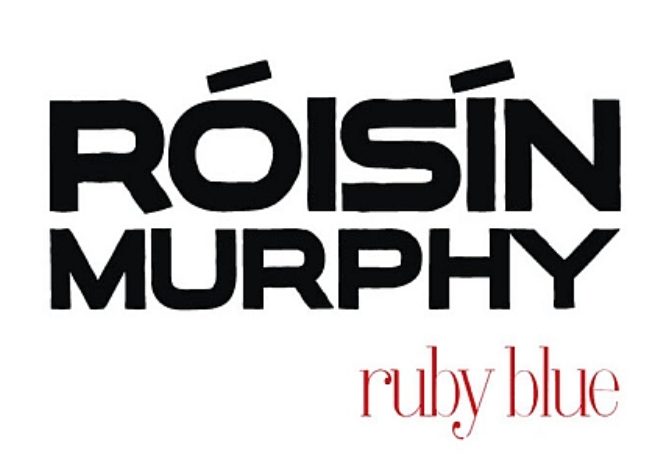
Róisín Murphys "Ruby Blue" - zwei Schriften gesucht
Ich suche die beiden Schriften des Albumcovers von Róisín Murphys "Ruby Blue" aus dem Jahr 2005, einmal eine Grotesk- (nur versal für Róisíns Namen verwendet) und eine Serifenschrift (Minuskel für den Titel).
In den Credits wurde Steffan MacMillan als Designer des sleaves angegeben.
Diesen habe ich auf Twitter gefunden.
Er ist einer der Gründer vom Alphabetclub und hat netterweise auf meine Anfrage reagiert. Mit diesem Stand der Dinge wende ich mich nun an euch, denn die Namen der Schriften konnte ich trotz "Urheber" nicht herausfinden.
Die Schriften stammen also laut Aussage MacMillans aus einem alten, französischen Magazin, welches er teilweise gescannt und für Namen und Albumtitel nachgezeichnet hat.
Es ist also anzunehmen, das es ebenso französische Schriften sein könnten. Ich persönlich würde vom Erscheinungsbild der Schriften einen Zeitraum von 1960er bis 1980er eingrenzen.
Da sie aus einem publizierten Magazin stammen, nehme ich an, dass diese auch irgendwo digital und somit kommerziell erhältlich sein müssten. Parallel zu diesem Beitrag werde ich die französischen Einträge im Type Foundy Archive durchforsten.
Eine Anmerkung: Je nachdem, wann genau das Magazin publiziert wurde, kann es durchaus sein, dass die Schrift nicht digital vorliegt, sondern beispielsweise im Fotosatz realisiert wurde. Das Wort MURPHY sieht übrigens sehr nach einer (etwas ungelenk) manipulierten Satzschrift aus, da würden sich recht schnell ähnliche Vorbilder finden lassen – aber nach dieser hast Du ja nicht gefragt, richtig?
Hier für die Kollegen der Einfachheit halber die Abbildung der gesuchten Schriften direkt eingebunden, das erleichtert die Suche:
Und bei der RÓSÍN erscheint es mir auch fraglch, ob es hierzu überhaupt passende Gemeine gibt. Ich habe ja schon einiges ähnliches umgesetzt, und da gibt es dann bei einigen Minuskeln echt Probleme, die in die Formensprache vder doch recht fetten Schrift zu prügeln. nAllerdings ist die Konstrultion dieser Schrift so deutlich in den vorhandenen Buchstaben erkennbar, das man son etwas wohl schneller komplett sauber zeichnet, als sie in Schriftverzeichnissen zu suchen.
Und wenn der Designer des Covers die auch schon lieber nachgezeichnet, oder sonst wie reproduziert hat - was dann zu diesem etwas ungelenken führt, denke ich, dass auch der schon vergeblich gesucht hat.
Ich muss da an die Schrift Good Times von Typodermic (1998) denken.
Die Schrift hat eine gewisse Ähnlichkeit und ich hatte die mal im Auge, eben weil ich nach so was wie einer Vorlage gesucht habe, aber über die grundlegenden Vorlagen und Ideen zur Good Times keinen Schritt und keine Schrift weiter gekommen bin. Ich war mir ziemlich sicher, das es eine Art Vorlage, wie Du sie hier gezeigt hast geben muss. Deine Vorlage ist für mich so was wie das "missing link", nach dem ich vor einigen Wochen erfolglos gesucht habe. Das wird Dir zwar nicht weiterhelfen, aber mir hilft Deine Anfrage weiter. Danke schön.
ähnliche schriftens gibts eigentlich wie sand am meer.
ich bezweifle das du genau diese zeichen als font finden wirst,
vorallem solange wir nicht erfahren ob es der titel oder eine
headlineschrift in diesem 'magazin' war, bzw. wie dieses hieß.
das an den buchstaben herumgeschnitzt wurde, sieht man ja
schon beim R.
Schade, natürlich. Der Designer meinte, man hätte ihm eben dieses alte Magazin "hingeworfen" und hat damit gearbeitet.
Die Good Times Heavy kommt dem ganzen sehr nahe!
Für den Albumtitel würde ich glatt eine neue Schrift der französischen Production Type die Familie Trianon benutzen, auch wenn die Serifen (vor allem die Füße) nicht waagrecht bleiben.
Ihren Namen muss ich dann eben auch nachzeichnen, mit der aktuellen Aufmachung habe ich gleiches getan (die ich übrigens auch sehr gelungen finde, aber das ginge ins Off-Topic).
Da bekäme ich doch echt lust, solche nicht-digitalen Schriften wiederzubeleben und groß zu träumen — so á la The Doves Type.